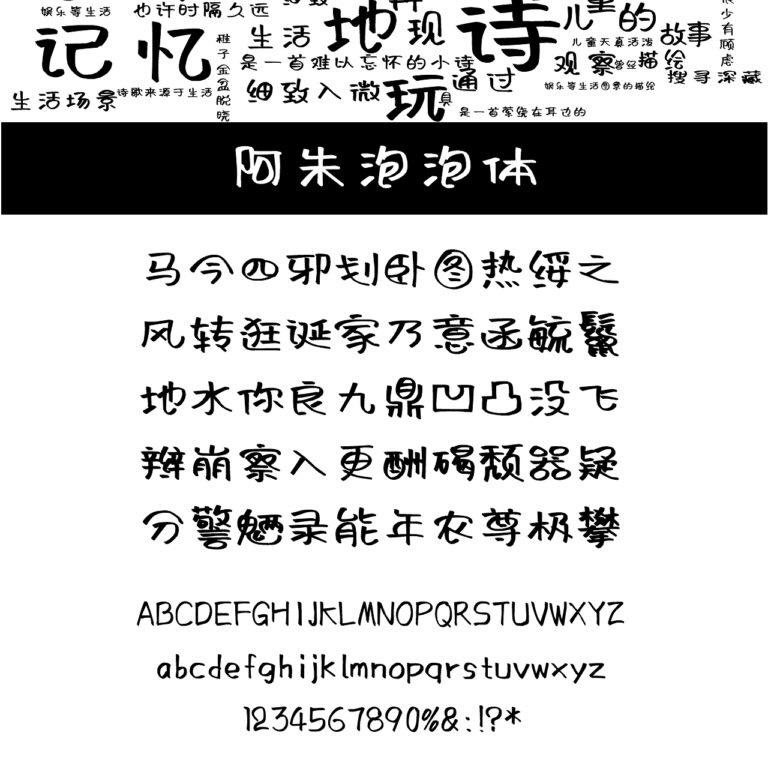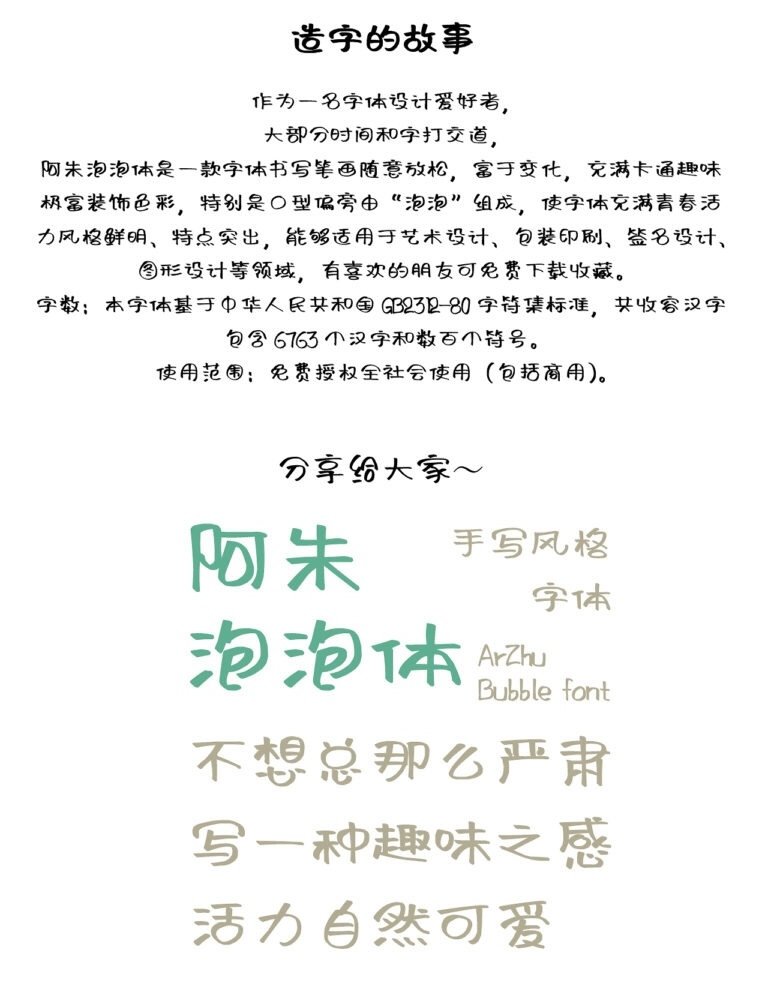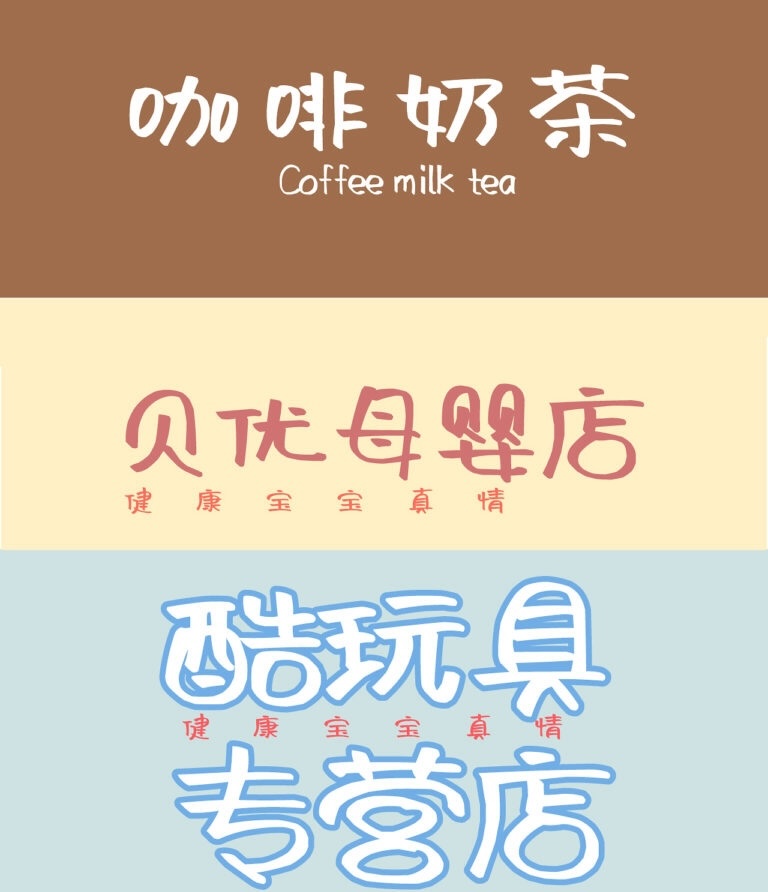
阿朱泡泡体
阿朱泡泡体发布于2019年光棍节,是一款风格极具辨识度的创意装饰字体,由阿朱字库推出,整体定位偏向年轻化、趣味化与视觉表达强化,适用于强调个性与氛围感的设计场景。
该字体最大的特点在于书写结构呈现出明显的随意性与松弛感,笔画不再遵循传统印刷字体的严谨比例,而是在保持识别度的基础上增加了更多变化与节奏感,使整体字形更具“手写式动态”。这种不规则的结构处理让字体在视觉上更具活力,也更符合当代年轻审美中对“轻松表达”的需求。
在细节设计上,阿朱泡泡体融入了大量卡通化与装饰性元素,尤其是部分偏旁结构采用“泡泡”造型进行替代与重构,使字体呈现出较强的趣味符号感。这种设计不仅增强了视觉记忆点,也让字体在标题设计、海报传播以及社交媒体视觉中具有更高的吸引力。
同时,字体整体风格偏圆润柔和,笔画转折处多采用圆角处理,弱化了传统字体的锐利感,使其在视觉情绪上更偏向轻松、友好与活泼。整体结构具有一定的夸张性与装饰性,使其在小红书、包装设计以及品牌年轻化表达中具有较强适配性。
从字符覆盖来看,该字体基于 GB2312-80 字符集标准构建,共收录约6763个汉字及常用符号,能够满足基础中文排版与商业应用需求,在实用性与视觉表现之间取得一定平衡。
综合来看,阿朱泡泡体是一款强调趣味表达与视觉识别的装饰字体,更适用于需要“情绪传达”和“风格强化”的设计场景,而非严肃长文本排版。